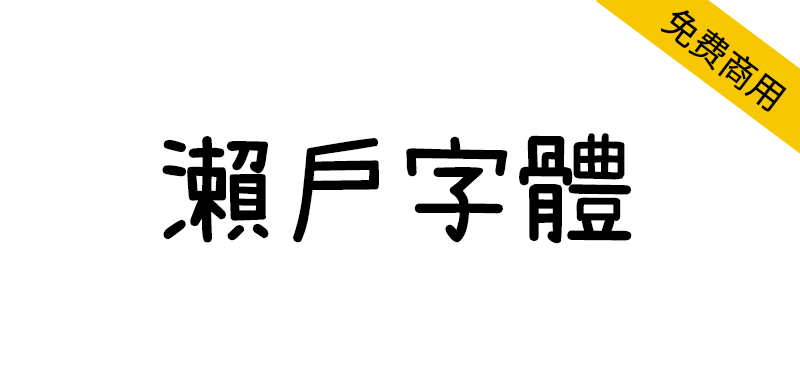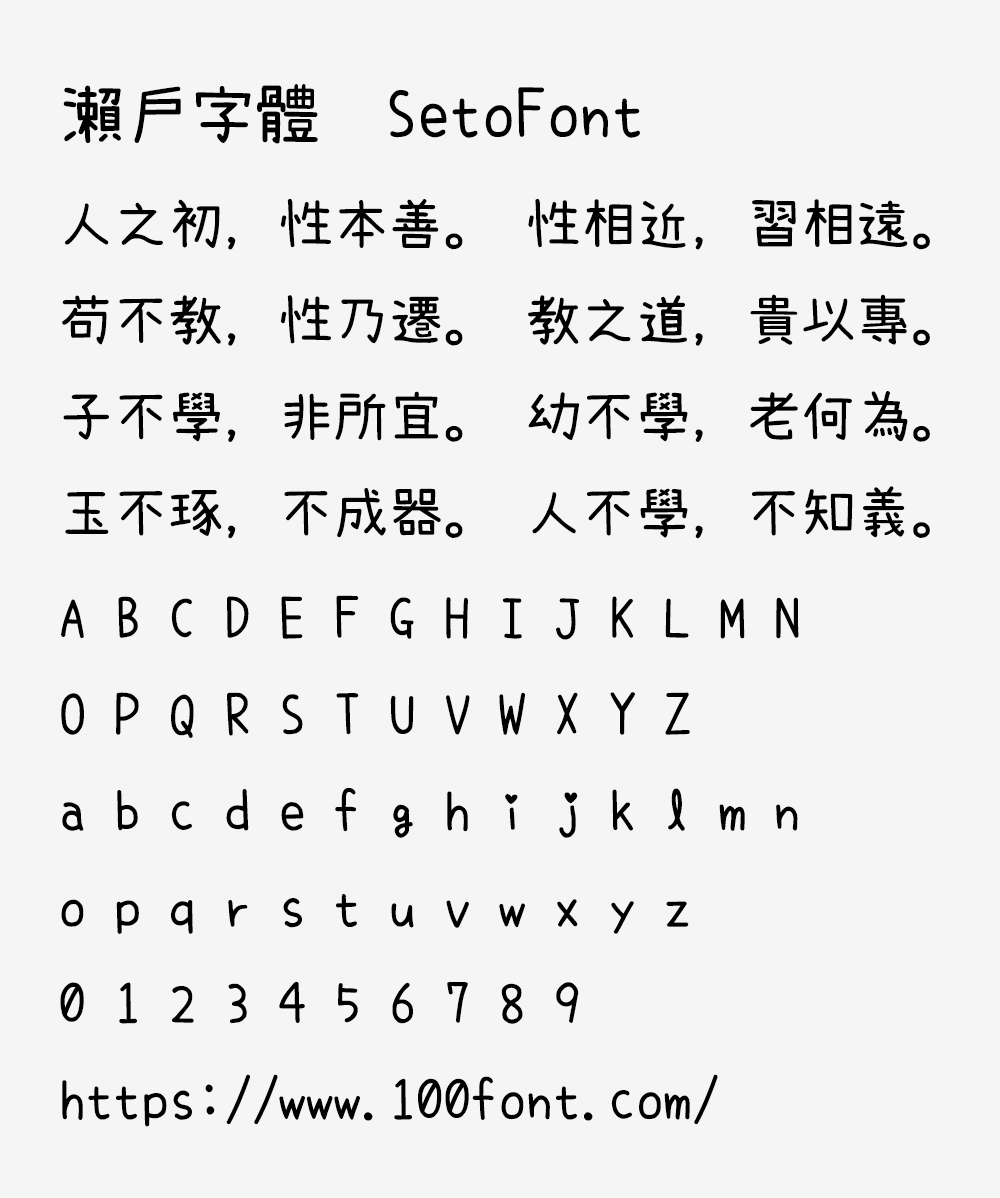
濑户字体(SetoFont),是一款偏可爱风的字体,是设计师个人手书,丝毫不造作,走的是一个好人缘天然呆的路线,甚至西文也很可爱,支持繁体中文、日文,包含CJK常用汉字、平片假名、JIS第一至四级,共30000余字。这是由日本的一位业余字体设计师(其实是以主妇的身份从事字体设计的)濑户のぞみ小姐所制作的。
濑户字体虽然支持中文,但是简体中文容易缺字,如果你喜欢这个字体,可以移步到cjkfonts 全濑体,cjkfonts 全濑体是一款基于濑户字体透过深度学习智能造字的字体,弥补了濑户字体没有的繁体及简体字。